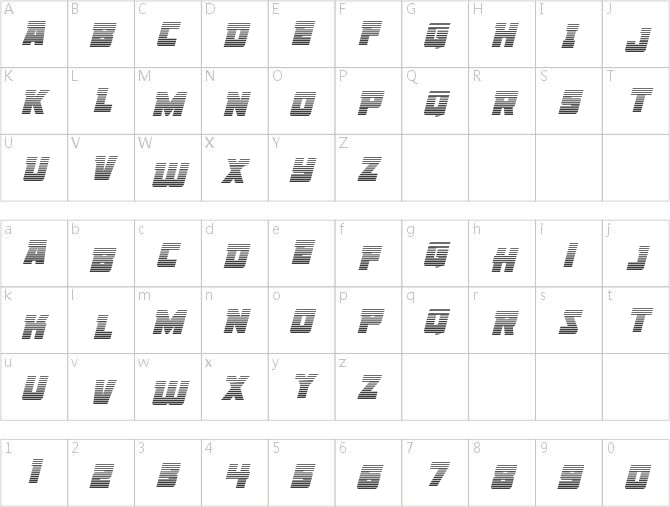
字體名稱: liberty
libertylegiongradital
libertylegiongradital介紹
libertylegiongradital字體字庫是一款讓人賞心悅目、百看不厭的英文字體,適合各類廣告和產品包裝設計應用,字體大小0.06MB,格式為ttf字體,上傳用戶是yinjun,作者/版權方為未知
libertylegiongradital效果圖